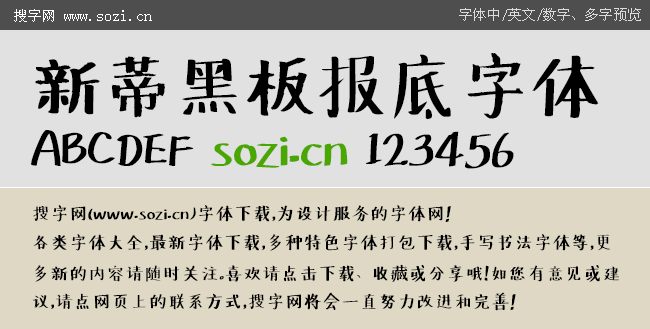
新蒂黑板報(bào)底字體
搜字網(wǎng)提供一款新蒂黑板報(bào)底字體中文字體下載,新蒂黑板報(bào)底字體是一款POP風(fēng)格的廣告字體,該字體整體效果為卡通風(fēng)格,非常有趣,可用于海報(bào)設(shè)計(jì)、兒童產(chǎn)品包裝、報(bào)刊雜志、繪畫創(chuàng)作等廣告設(shè)計(jì)場(chǎng)合使用,喜歡的朋友快下載收藏吧。